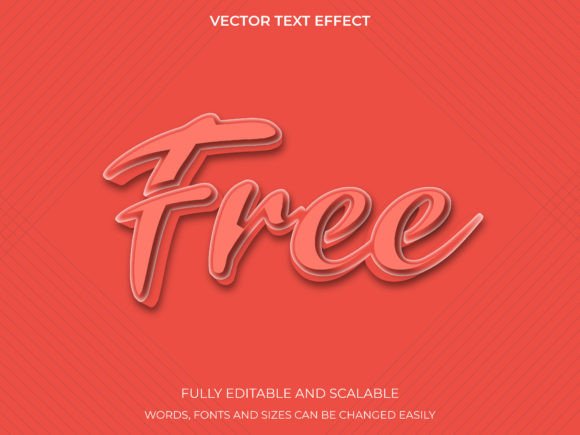
Text Effect in 3d Next Free Font Style
Mencari elemen reka bentuk yang sesuai boleh menjadi mencabar, tetapi Text Effect in 3d Next Free Font Style menawarkan koleksi luar biasa yang menaik taraf karya anda serta-merta.
Sama ada anda mencipta produk POD (Print on Demand), jemputan perkahwinan atau grafik media sosial, Text Effect in 3d Next Free Font Style amat bersesuaian.